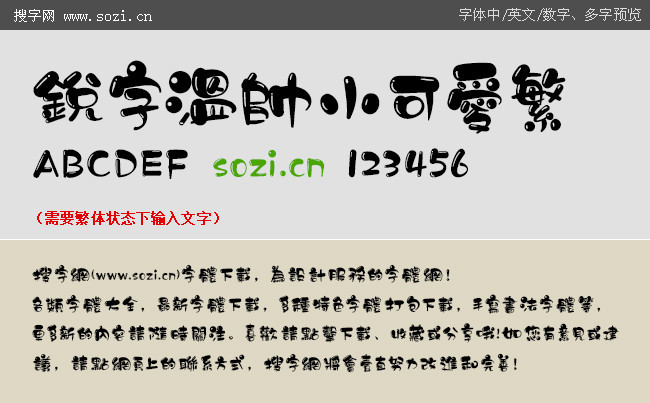
銳字溫帥小可愛(ài)繁
搜字網(wǎng)提供一款銳字溫帥小可愛(ài)繁中文字體下載,銳字溫帥小可愛(ài)繁在可愛(ài)體的基礎(chǔ)上添加了高光,更加有立體感。字形溫潤(rùn)飽滿(mǎn)、親切乖巧,筆畫(huà)不拘一格、粗細(xì)對(duì)比協(xié)調(diào)、簡(jiǎn)化變形有新意且不失識(shí)別性,營(yíng)造了一種輕松歡快、充滿(mǎn)趣味性的氛圍;非常適合兒童海報(bào),包裝設(shè)計(jì),網(wǎng)頁(yè)設(shè)計(jì)等設(shè)計(jì)使用。【本字體供個(gè)人非商業(yè)免費(fèi)使用,如需商用請(qǐng)聯(lián)系作者授權(quán)】